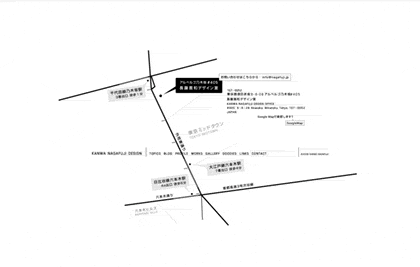
nagafuji design et typo in motion
une symphonie graphique en motion
qui n’est pas sans rappeler les travaux de Maeda!
Du savoir-faire technique à la narration,
il y a encore un pas à franchir
mais je ne doute pas un instant que
c’est la prochaine étape.
Logos un peu mode,
un peu surfaits, mais toujours très purs.